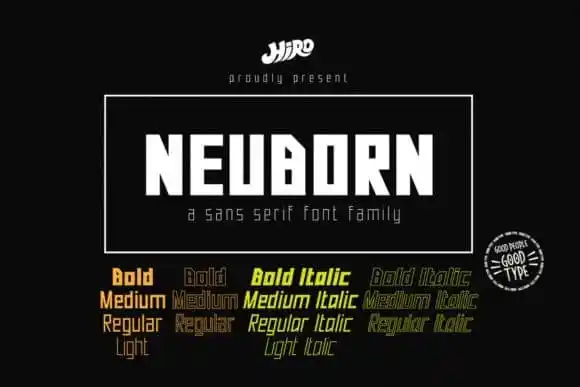
Introduzimos Neuborn Display Font, uma tipografia geométrica marcante e forte. Seu primeiro impacto visual é a forma retangular com as bordas rígidas e afiadas, criando um aspecto poderoso que chama atenção imediatamente. O designer HIRO.std criou este design avançado, projetado para se adequar a uma grande variedade de projetos. Inclua Neuborn Display Font em suas ideias criativas, e você verá como ele as destaca. Ideal para ambientes que buscam um estilo assertivo e dinâmico, seja para gráficos de marketing, sites profissionais ou qualquer outro tipo de projeto visual, esta fonte está certa para destacar sua marca.